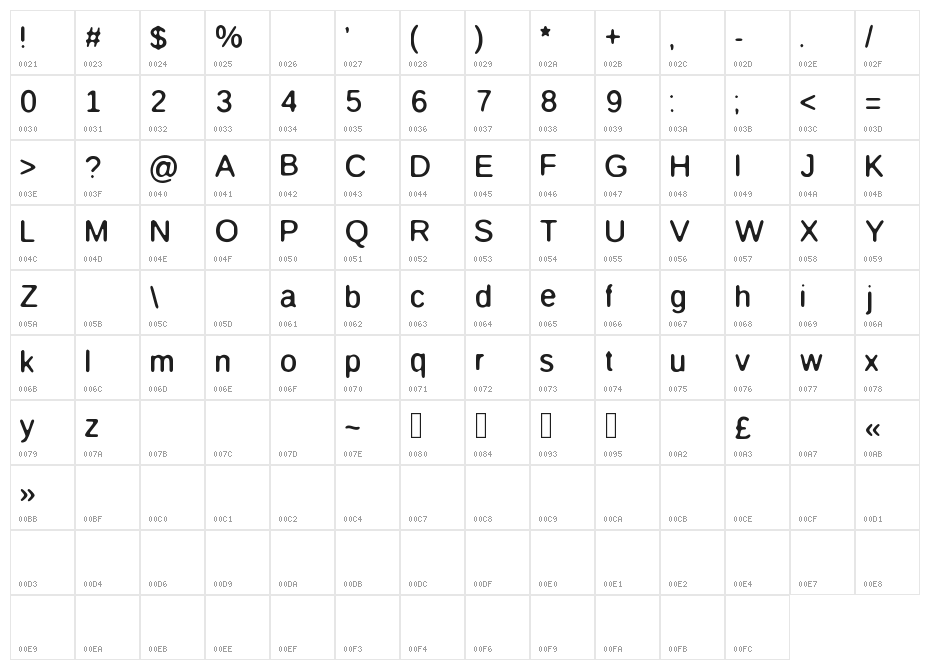
MAW Font
| حالة الاستخدام | Headlines, Body text, Logos |
| مشاريع مقترحة | Ideal for branding, signage, user interfaces, and educational materials due to its clarity and modern appeal. |